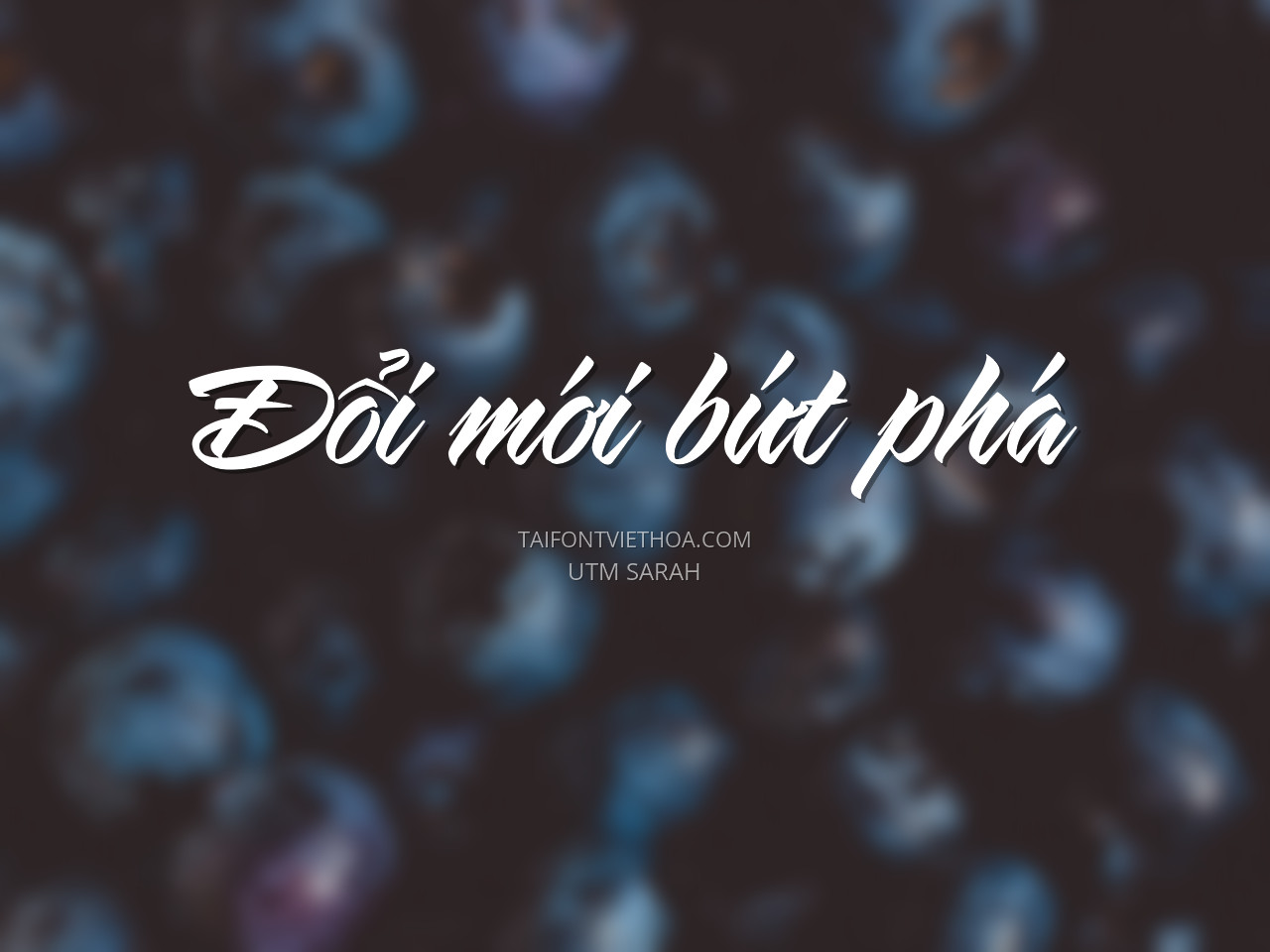
Giới thiệu về font UTM Sarah
UTM Sarah là phiên bản Việt hóa của font Sarah – một kiểu chữ script mềm mại, thanh lịch và đầy nữ tính, được thiết kế dựa trên phong cách viết tay tự nhiên và bay bổng. Font gốc nổi bật với các nét bút uyển chuyển, mượt mà và tinh tế, rất phù hợp cho các dự án thiệp cưới, branding và thiết kế cá nhân hóa. Phiên bản Việt hóa đã được hoàn thiện để hỗ trợ đầy đủ tiếng Việt cùng hơn 100 ngôn ngữ khác, giúp mở rộng phạm vi sử dụng trong nhiều dự án sáng tạo.
Font UTM Sarah được taifontviethoa.com sưu tầm và lựa chọn kỹ lưỡng nhằm phục vụ cộng đồng thiết kế Việt Nam. Phiên bản Việt hóa giữ nguyên nét mềm mại, duyên dáng và tinh tế của bản gốc, đồng thời tối ưu khả năng hiển thị tiếng Việt, rất phù hợp cho các dự án thiệp cưới, thiết kế nghệ thuật và truyền thông cá nhân hóa.
Đặc điểm thiết kế và ứng dụng của UTM Sarah
UTM Sarah sở hữu cấu trúc script với các nét bút thanh mảnh, liên kết tự nhiên và đa dạng ligature giúp tăng tính linh hoạt và biểu cảm trong thiết kế. Font có độ tương phản nhẹ nhàng, tạo cảm giác mềm mại, duyên dáng và sang trọng, rất thích hợp cho các thiết kế mang phong cách cá nhân hóa và nghệ thuật cao.
Font thích hợp sử dụng trong các ứng dụng như thiệp cưới, thiệp mời, thiết kế logo thương hiệu mỹ phẩm, poster nghệ thuật, bao bì sản phẩm thủ công và các dự án truyền thông mang tính cá nhân hóa cao. Các ngành nghề phù hợp gồm: tổ chức sự kiện, thời trang, làm đẹp, nghệ thuật sáng tạo, quảng cáo cá nhân hóa và thiết kế nội thất.